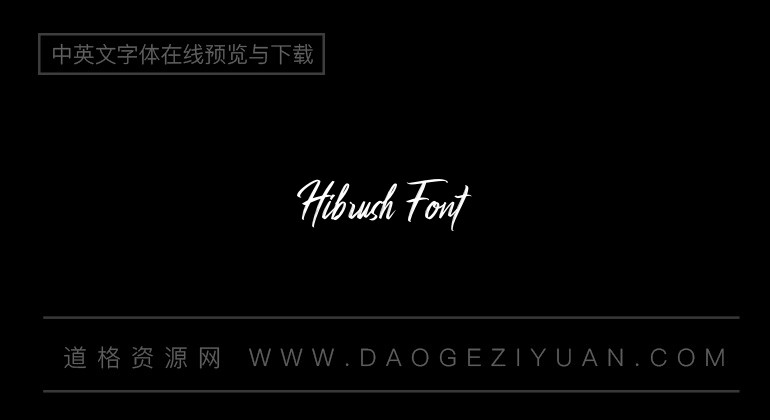
Hibrush Font 是一种手写风格的字体,其特点是有着流畅自然的笔画和轻松愉悦的氛围。它是由设计师 Alifinart Studio 创作的,适合用于印刷品、海报、标志及其他设计项目中。Hibrush Font 字体家族包括加粗、正常和斜体三种类型,可以满足不同尺寸和设计需求。内容介绍
Hibrush Font是一款非常不错的手写艺术字体,具有很好的视觉感,适合于文化类的宣传设计、商业类品牌的广告和产品包装设计以及个性化文字排版等较多场景。